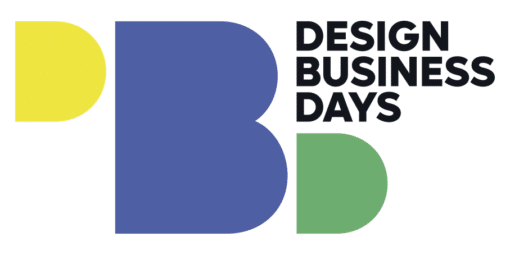
Neues Buch »Big Type«
Mit großen Buchstaben schaffen sich die in »Big Type« gezeigten Arbeiten Gehör im visuellen Rauschen.
Typoillustrationen, gerne auch großformatig, sind eine schöne Abwechslung in der visuellen Landschaft. Genau diesen Projekten widmet sich das gerade erschienene Buch »Big Type«, herausgegeben von Counter-Print, Verlag und Onlinestore für Designbücher (224 Seiten, 20 Pfund, ISBN 978-1-8381865-7-9). Die gezeigten Arbeiten sind überwiegend experimentell, spielen mit Schrift und stellen diese in den Mittelpunkt. Da gibt es etwa von der mexikanischen Agentur Futura aufblasbare Buchstaben, die einen ganzen Raum füllen, vollgeschriebene Häuserwände von Anthony Burrill oder das typografische Branding für das London Design Festival von Pentagram.
Brandneu sind die ausgewählten Projekte alle nicht – Büchermachen braucht eben Zeit. Inspirierend aber ist »Big Type« in jedem Fall, zumal es neben den Abbildungen Interviews mit Kreativen und ein Vorwort von Counter-Print-Gründer Jon Dowling gibt. Wer das Buch bestellt, kann zwischen einem grau-gelben, blau-roten oder grün-orangefarbenen Cover wählen.